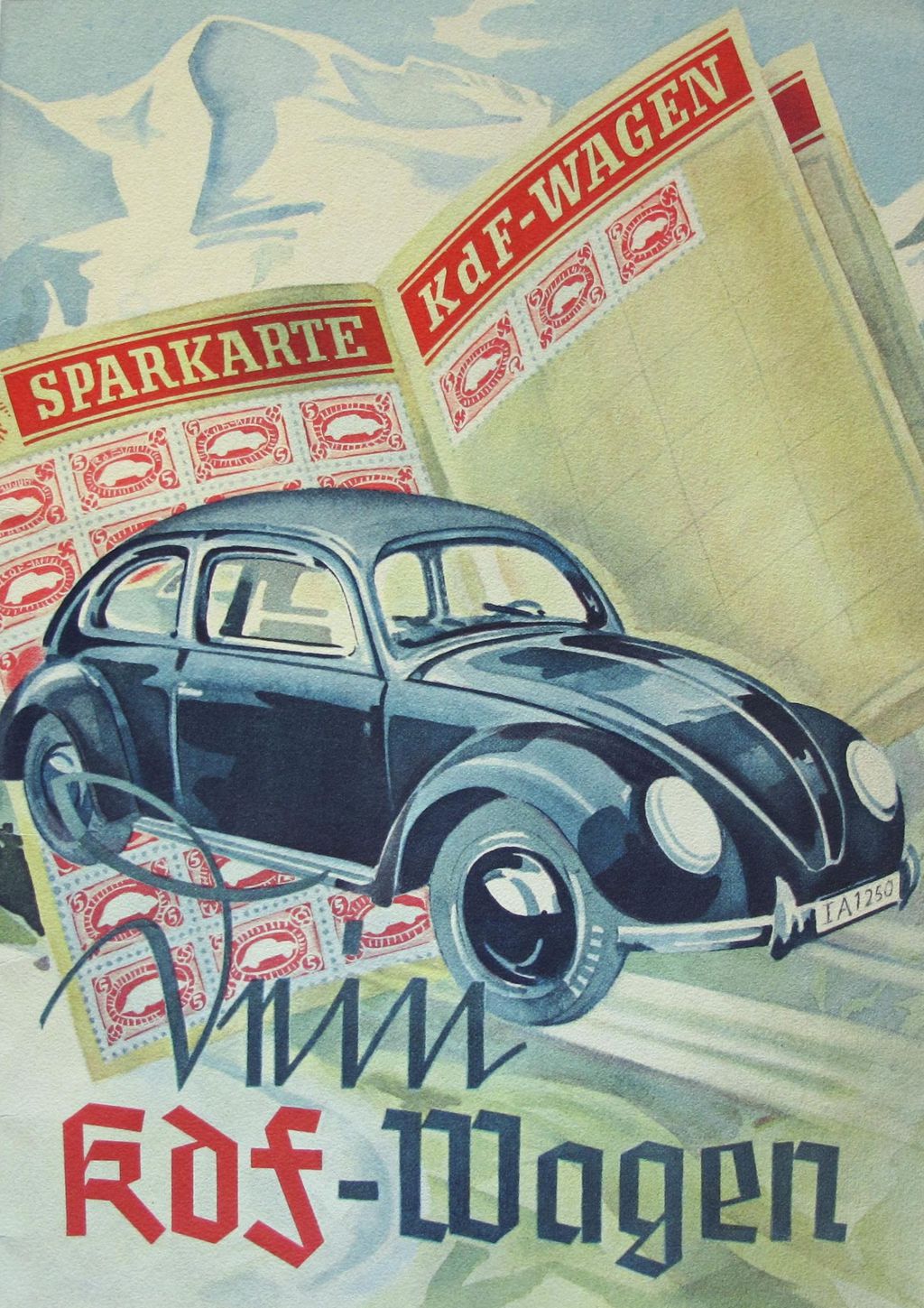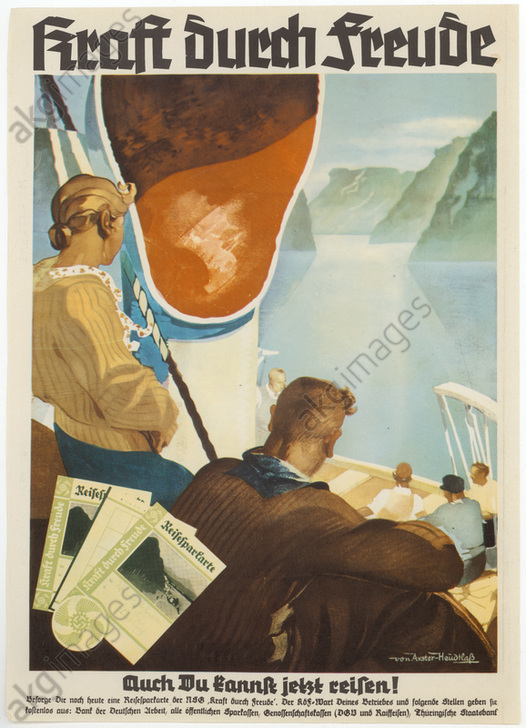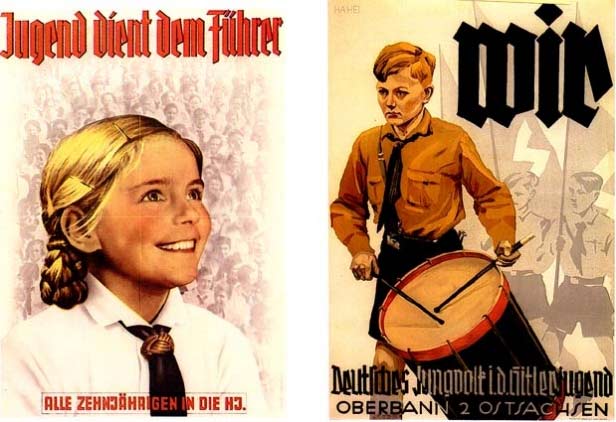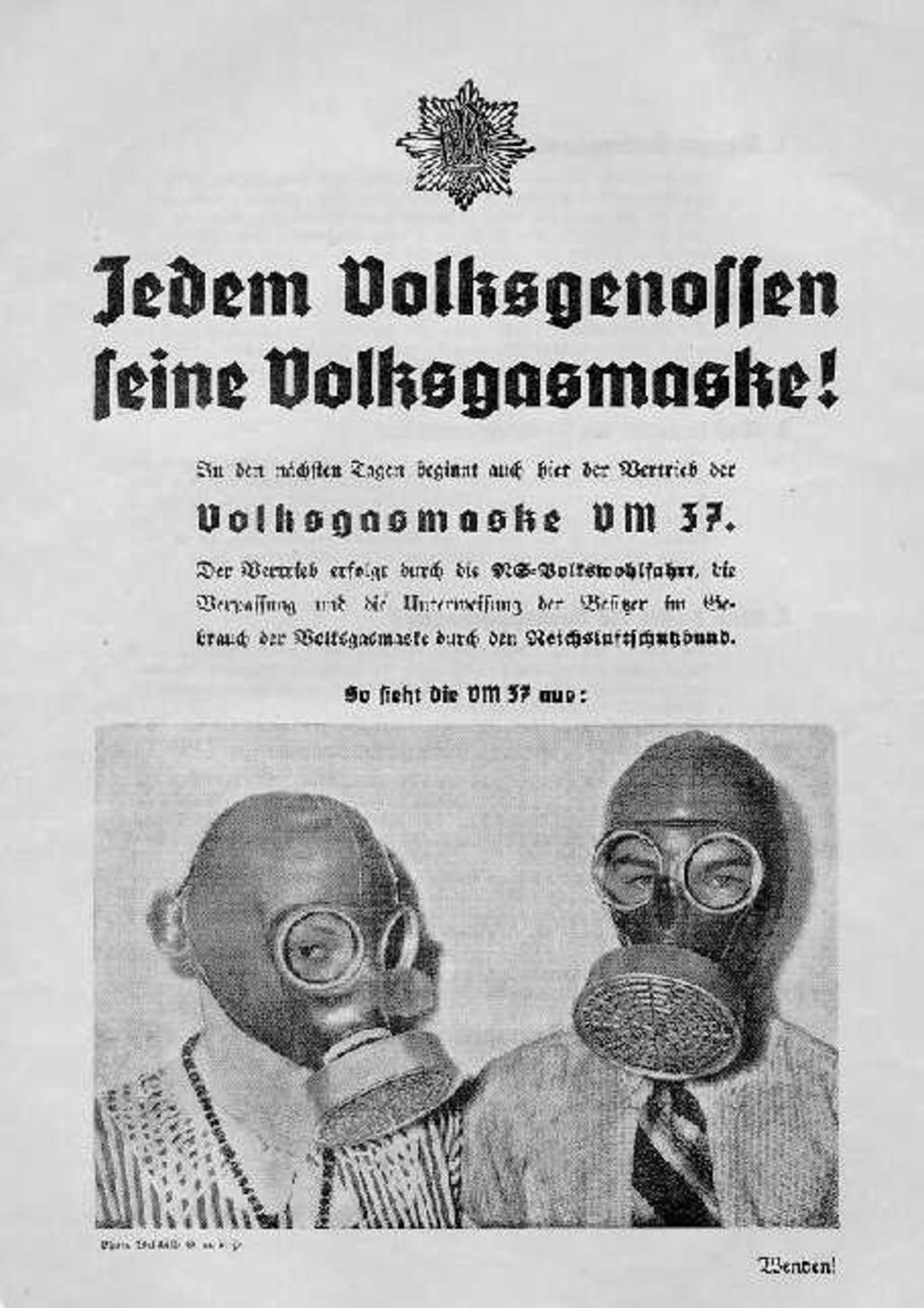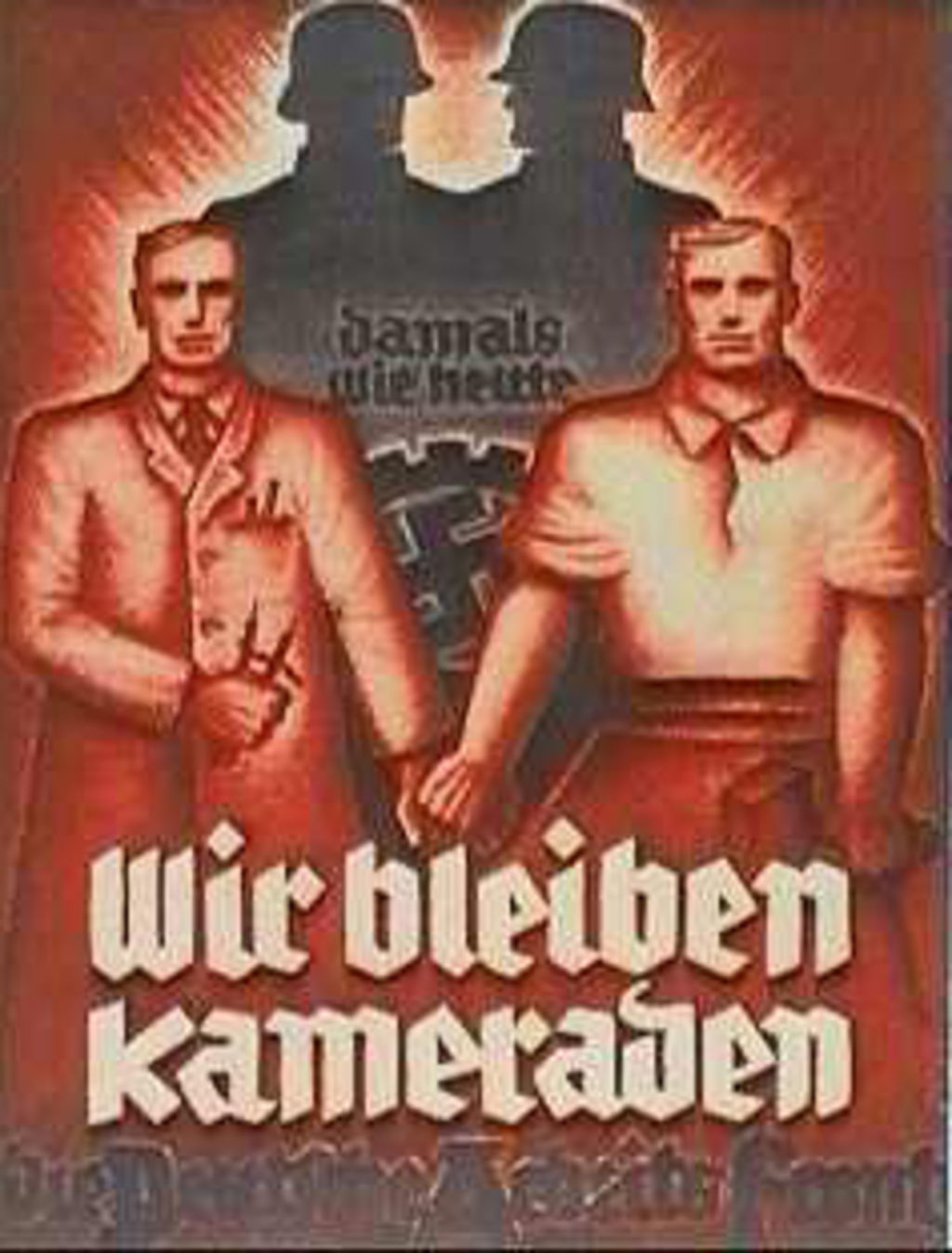
Schriftmuster Tannenberg
„Schaftstiefelgrotesk ist eine umgangssprachliche Bezeichnung für gebrochene Groteskschriften (siehe zugehöriger Wiki-Artikel).
Schriften dieses Stils erschienen ab 1933 mit betont nationalistischen Namen wie Tannenberg (nach der Schlacht bei Tannenberg), National, Großdeutsch etc. und kamen in Schaugrößen-Anwendung auch für nationalsozialistische Propaganda zum Einsatz. So wird der Begriff »Schaftstiefelgrotesk« mitunter auch in einem polemischen Zusammenhang gebraucht,
um die gebrochenen Grotesken auf diese Funktion zu reduzieren. Eine allgemeine  Einordnung als »Nazi-Schrift« ist auf Grund der inhaltlichen, zeitlichen und örtlichen  Verknüpfnung mit den Nationalsozialismus naheliegend. Diese ideologische Behaftung der Schriften wird aber auch kritisch gesehen. Sie würde den Schlichten Gotischen nicht gerecht. Vielmehr sei die Verknüpfung der »typographischen Gene« der häufig barock verzierten gebrochenen Schriften mit denen der modernen Groteskschriften eine naheliegende Entwicklung die sich auch vor einem anderen gesellschaftlichen Hintergrund hätte ergeben können.
Bekanntester Vertreter einer Verwendung der Schlichten Gotisch bis in die Gegenwart ist das allgemeine Apotheken-Logo in Deutschland.
Urfassung: Ernst Paul Weise (1936)
Hans Peter Willberg schreibt im Buch »Fraktur« (Hermann Schmidt Verlag Mainz, 1993),
dass »der Setzervolksmund« schon in den 1930er-Jahren von Schaftstiefelgrotesk sprach.“
Was daran soll jetzt dabei bitte einseitig oder geschichtsverzerrend sein? Hab mehrfach betont, daß die Googlebilder für sich natürlich nicht beweisträchtig sind. Aber warum soll ich sie wegleugnen? Auch hier: jedes Bild für sich ist ein Faktum. Jedes einzelne Bild für sich ist unrelevant. Erst wenn Häufungen gewisse Auffälligkeiten zu Tage fördern lohnt es sich dann genauer hinzuschaun. Und dann kommen eben all die anderen mehrfach aufgezählten Fakten(!) dazu. Jedes für sich singulär auftretend würd keine Sau jucken. Die Summe all der Fakten aber manifestiert meine Meinung.
Und genau damit bist du eben der Geschichtsverzerrung aufgesessen, denn gerade die Häufung der Propaganda-Plakate und darin wieder die Häufung in gebrochener Schrift spiegelt eben absolute nicht die Plakatierung der frühen 1930er Jahre wieder, sondern stammen von hunderten Webseitzen, die jeweils für die Darstellung der Nazi-Propaganda ganz gezielt nach möglichst drastischen Plakaten, und hier eben denen, die besonders "Nazihaft" aussehen für ihren Beitrag auf ihrer Seite ausgewählt haben.
und wenn du dann in der hier gezeigten Häufung bestimmter Stile, und das eben nur auf Propagandaplakaten der Nazis dir einen unumstößlichen "Fakt(!)" zusammenbaust, ist das eben keiner.
Statt dessen dominierten die Ankündigungen der hunderten Tanzlokale, und denen unzählige Tanzkapellen wechseld auftraten, die damals durch Deutschland tourten, die Werbung für die "Weiße Woche" bei Wertheim, die Hustenbonbons und Zigaretten, das Programm der Theater und Kinos der Stadt die Plakatwände und Litfaßsäulen, schließlich gab es kein Fernsehen und keine Discos, man ging aus zum Tanzen, und musste sich informieren, wo es etwas interessantes gab.
Von all diesen Plakaten findet sich vielleicht ein unleserlichers Bild auf irgend einer Straßenansicht, aber eben nichts in den Google-Bildern. Aber gerade diese verlorenen Plakate zeigten wohl sehr deutlich die Schriftmode der Zeit, die dann natürlich auch von den Grafikern aufgegriffen wurde, die dann die Propagandaplakate gestalteten.
Und so, wie du jetzt aus der Masse der eindeutig gezielt gefilterten Bilder dein Geschichtsbild aufbaust und daraus schließt, das dies "Fakten(!)" sind, wärst du mit sicherheit auch damals den von den Nazis gelieferten "Fakten(!)" aufgesessen, denn auch hier wurde die Schuld der Juden an der Misere des Landes durch in gleicher Art sich selbst untermauernden Fakten dargestellt, die eben durch die allgegenwärtige, ständige Wiederholung genau so logisch als Fakt empfunden wurde, wie du aus den vielen Bildern schließt, die schlichte Fraktur wurde zunächst nur von den Nazis verwendet, und später den Kulturschaffenden aufgezwungen. Entschuldige, aber das ist kein "Fakt (!)" sondern Bullshit (!!)
Entschuldige, aber das ist kein "Fakt (!)" sondern Bullshit (!!)
Klar entschuldige ich. merk schon, Ralf hat nicht geübt mit Dir. Komm aber langsam an meine sprachlichen Grenzen Dir klar zu machen, was eigentlich ne simple Selbstverständlichkeit ist.
Also: Wir beide sitzen am Tisch. Wir haben ein Plakat da liegen. Von einem Geflügelzuchtverein. Dieses Plakat vor uns, es ist ein Faktum weil ich davon ausgehe, daß wir beide gerade nicht im Delirium sind. Und genau das mein ich als Fakt(!). Das was gerade da ist. Auch das Google-Plakat auf dem Bildschirm. Es ist da als Abbild. Es ist ein Fakt, daß das da ist auf meinem Bildschirm. Es ist nicht unbedingt Fakt (wenn auch wahrscheinlich), daß es physisch auch existiert. Wenn da jetzt eine Schaftstiefel drauf ist, dann ist es Fakt, daß auf dem Abbild der Googelsuche eine Schaftstiefel drauf ist (vorausgesetzt, daß ich immer noch nicht im Delirium bin). So hab ich Fakten aufgezählt. Ich habe nie behauptet, daß aus der Summe der vorliegenden Fakten ich zu dem Schluß käme, daß es ein Faktum wär, daß die Schaftstiefelgrotesken ein Produkt der  Nazi-Ideologie sind.
Ich sag (und schreibe mich langsam ins Delirium) daß bei der Summe der vorliegenden Fakten (die meisten davon hast ja auch du nicht bestritten) es für mich naheliegend ist daß die Entstehung der Schaftstiefeln ideologisch motiviert war.
Die Machart und das Werkzeug, steht in enger Beziehung zu den Intentionen die einem Werk zu Grunde liegen.
Gerade deswegen kann ich aber nicht eine Art und Weise der Ausführung pauschal als negativ hinstellen.
Es gibt sicherlich viele sehr gute Schriften, die am Reißbrett entstanden. Das sind i. d. R. nicht Renaissance-Antiquas.
Auch wenn mir die Schaftstiefelgrotesk genau so wenig wie dir zusagt,  habe ich kein Problem mit Schriften die konstruiert und „am Reißbrett“ entstanden sind.